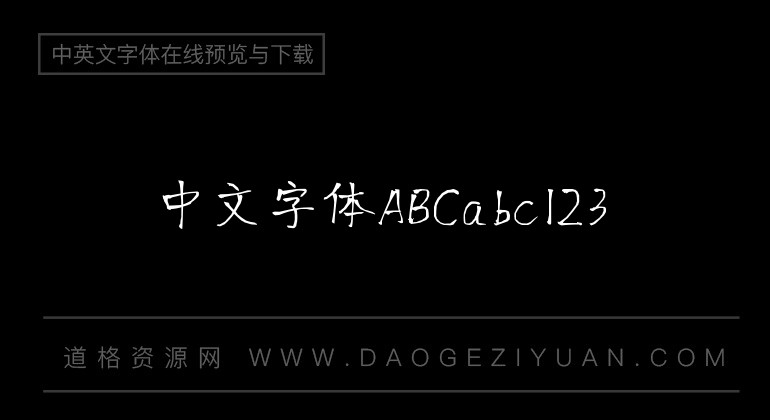
王强书法体是中国书法家王强先生所创作的一种书法字体,它是王强先生多年书法创作的结晶,融合了楷、行、草、篆、隶等多种文字风格的特点,是一种大气、端庄、流畅的书法字体。 王强书法体的字形丰富多样,笔画遒劲有力,每个字都具有独特的个性和美感,既有中国传统书法的气韵,又有现代设计的时尚感。它的笔画流畅自然,字形秀美优雅,给人以一种舒适的感觉。 王强书法体在设计上注重平衡和谐、形神兼备,不仅适用于中国传统文化领域,也可以应用于现代设计、广告、包装等多个领域。它是中国书法艺术和文化传统与时代精神的完美结合,具有很高的艺术价值和实用价值。文件名:WangQiangShuFaTi-2.ttf
王强书法体是一款非常不错的手写艺术字体,具有很好的视觉感,适合于文化类的宣传设计、商业类品牌的广告和产品包装设计以及个性化文字排版等较多场景。